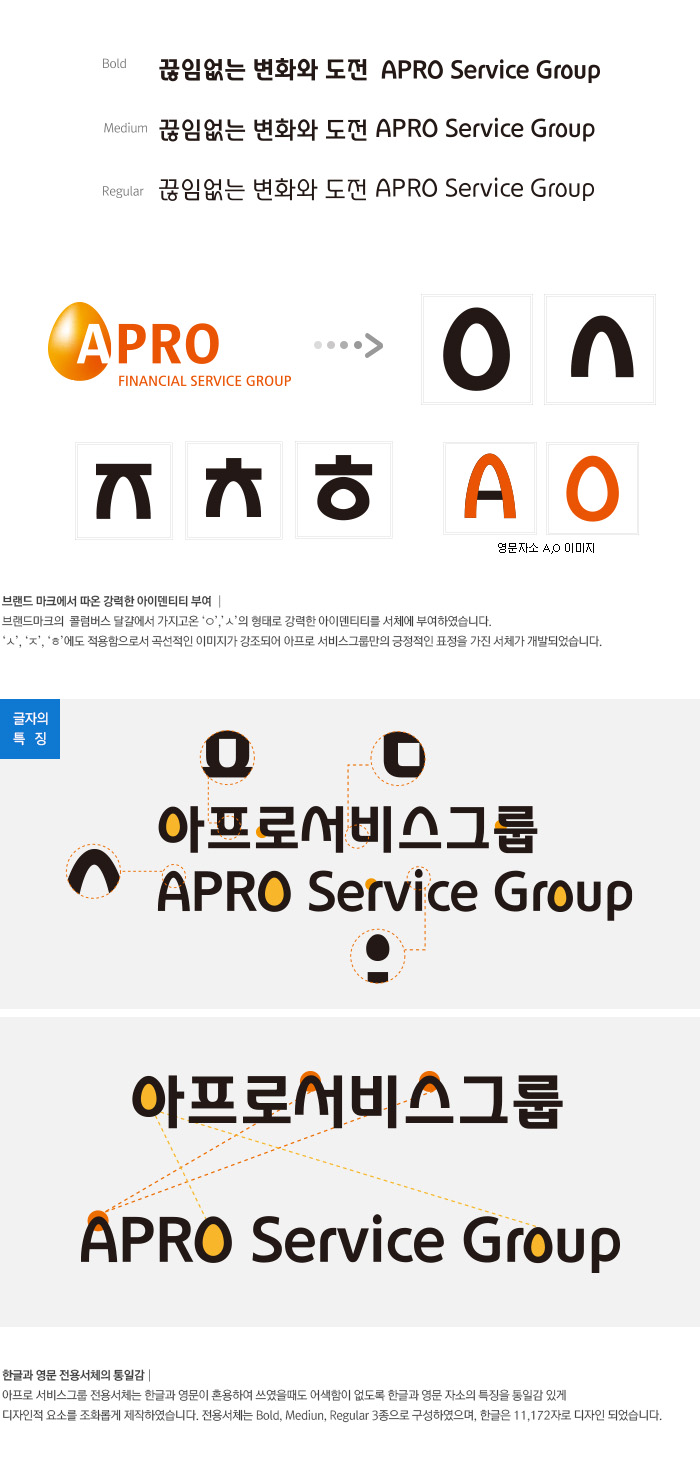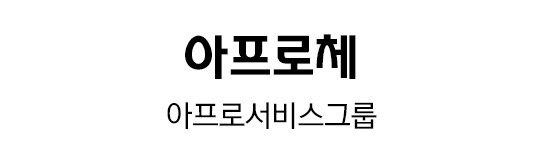
콜럼버스 달걀의 형태를 닮은 브랜드 마크에서 착안한 자소 디자인과 곡선적인 이미지을 강조하여 아프로서비스그룹만의 긍정적인 표정을 가진 서체로 개발했습니다.
| CLIENT | 아프로서비스그룹(現 OK금융그룹) |
| 프로젝트명 | 아프로서비스그룹 전용서체 'APRO' |
| 스펙 |
한글 11,172자 / 영문 94자 / 약물 986자 3종(Regular, Medium, Bold) |
| 개발연도 | 2016 |